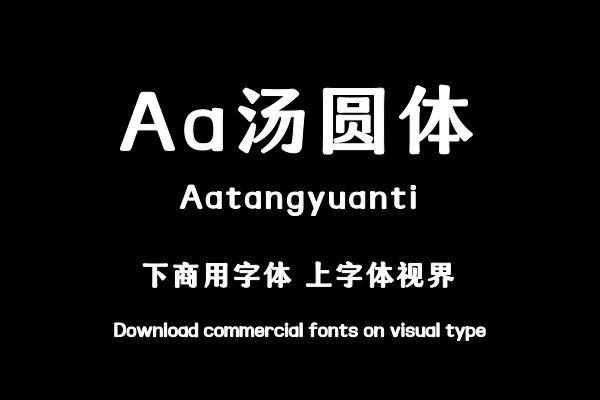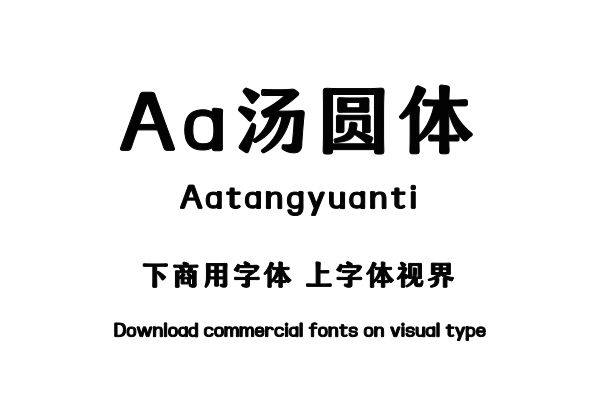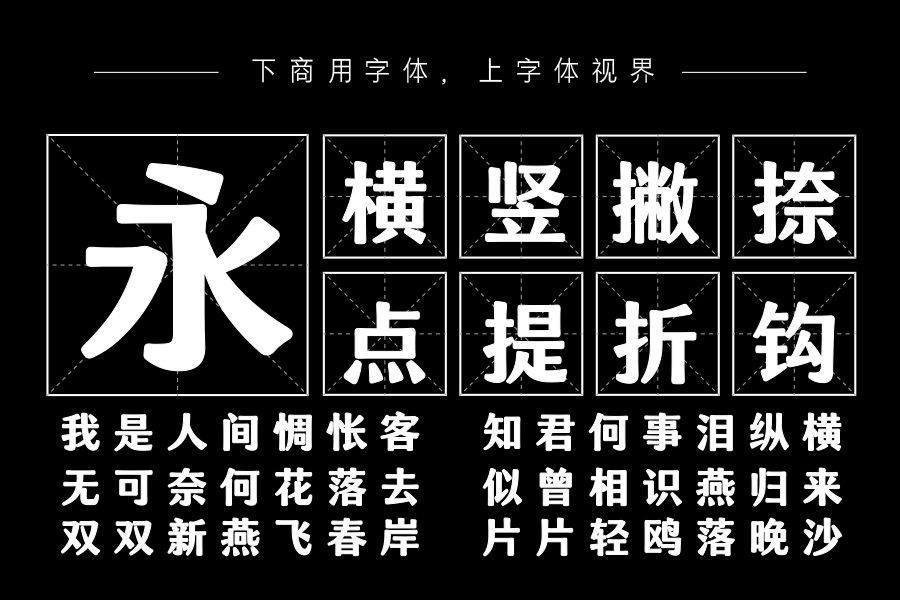
该字体创作时注重笔画的“美味感”,设计了带圆角的微妙的喇叭口,使其看起来柔软温润而富有弹性;横细竖粗的笔画使其错落有致,中和了圆体的甜腻感,更加清爽简约,就如同......购买须知:“下载服务费”与“字体VIP”所获得字体 仅用于个人非商用, 商用请联系付费授权。本字体为电脑用字,手机没有root权限不支持直接手机换字(手机如何root,请自行百度搜索教程)。购买前请先 了解清楚后再付款 ,字体为虚拟产品无法回收 一旦购买不支持退款。